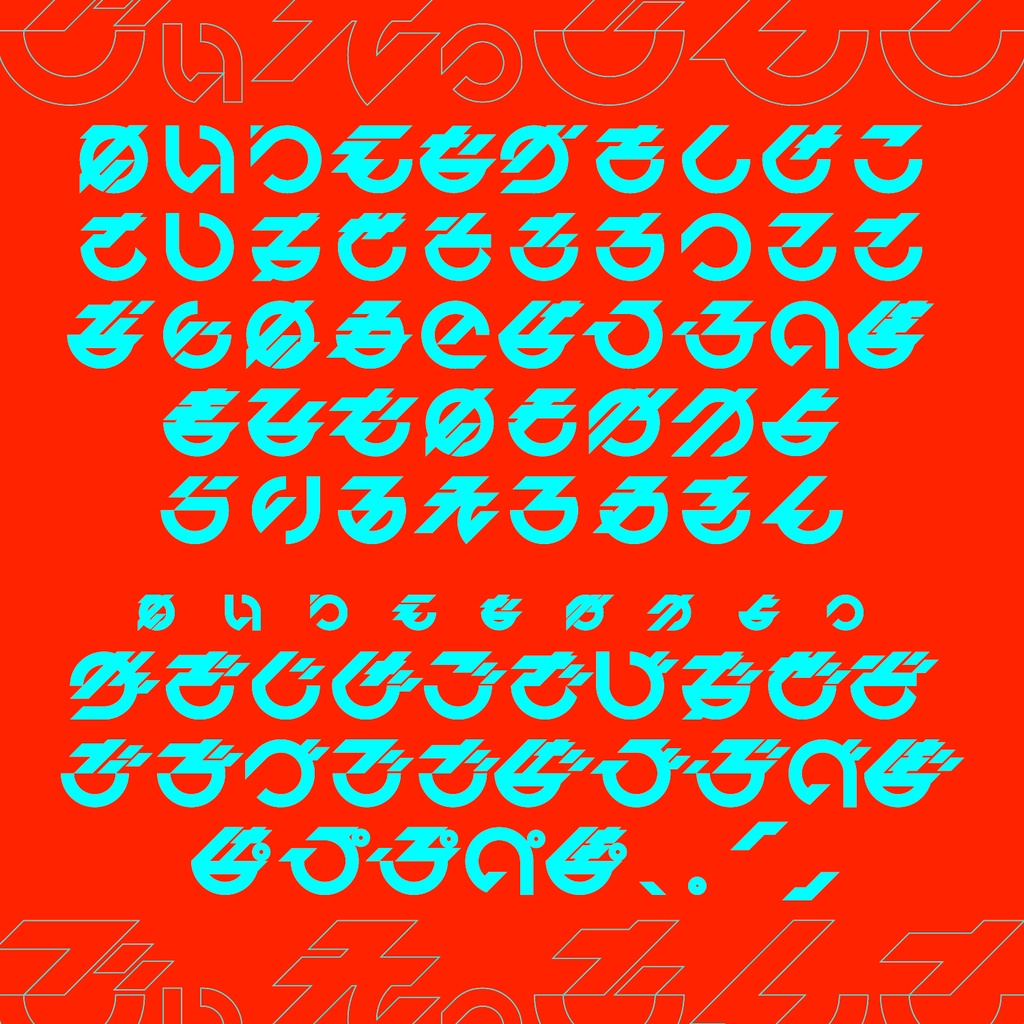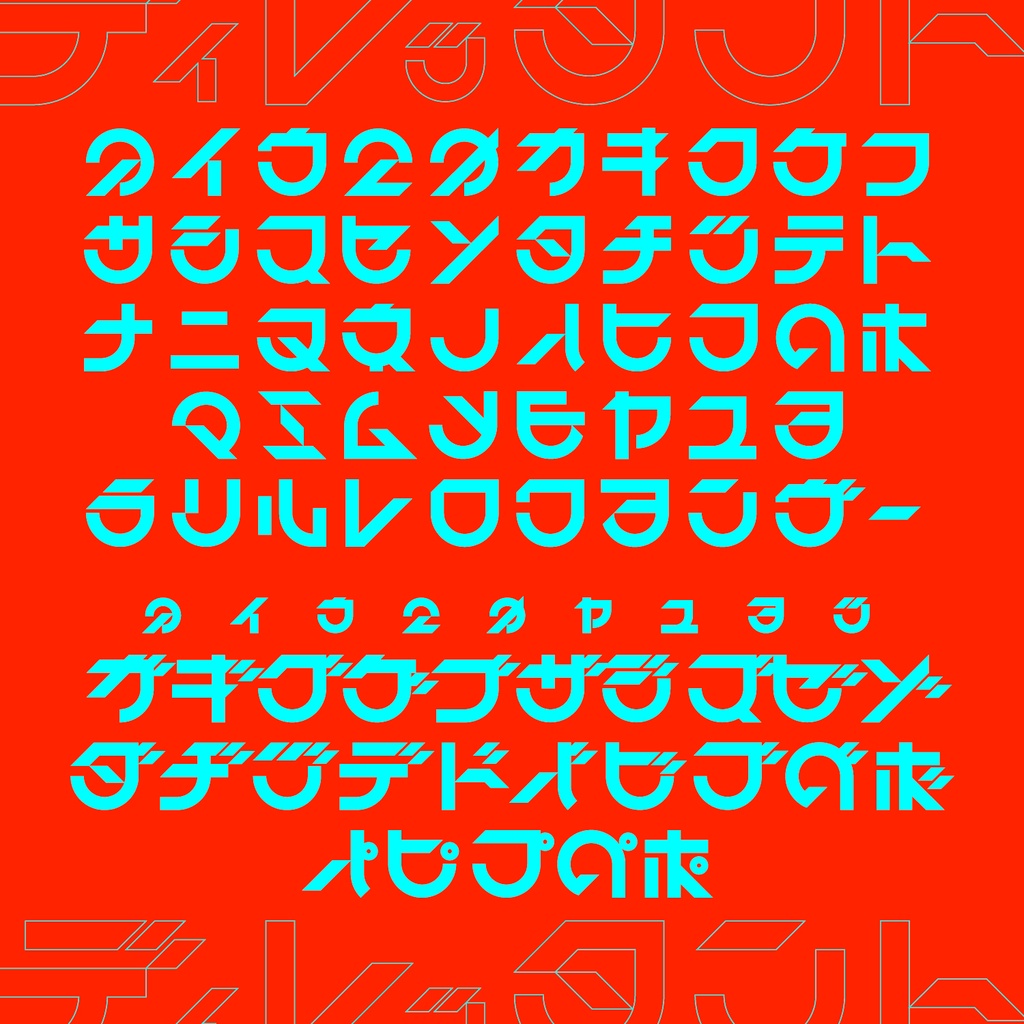
【フリーフォント】でぃれったんと
読めなさそうで読めるかもしれない ちょっとクセのある文字。 好事家な人へ送るオリジナルフォントです。 デザインのあしらいとしても使えます。 好事家(こうずか)=ディレッタント 意味:ものずきな人。 ※収録文字は「ひらがな・カタカナ・数字・一部記号」となっています。 ◆ライセンス 個人や商用利用を問わず、無料でお使いいただけます。 使用の際の報告などは不要ですが、ご連絡いただけると嬉しいです。 著作権は放棄しておりません。 ◆禁止事項 ・フォントファイルの再配布や、販売。 ・こちらのフォントを使用したロゴや制作物の商標登録。 ◆注意事項 フォントを使用したことにより生じた損害について 製作者は一切の責任を負いませんのでご了承ください。